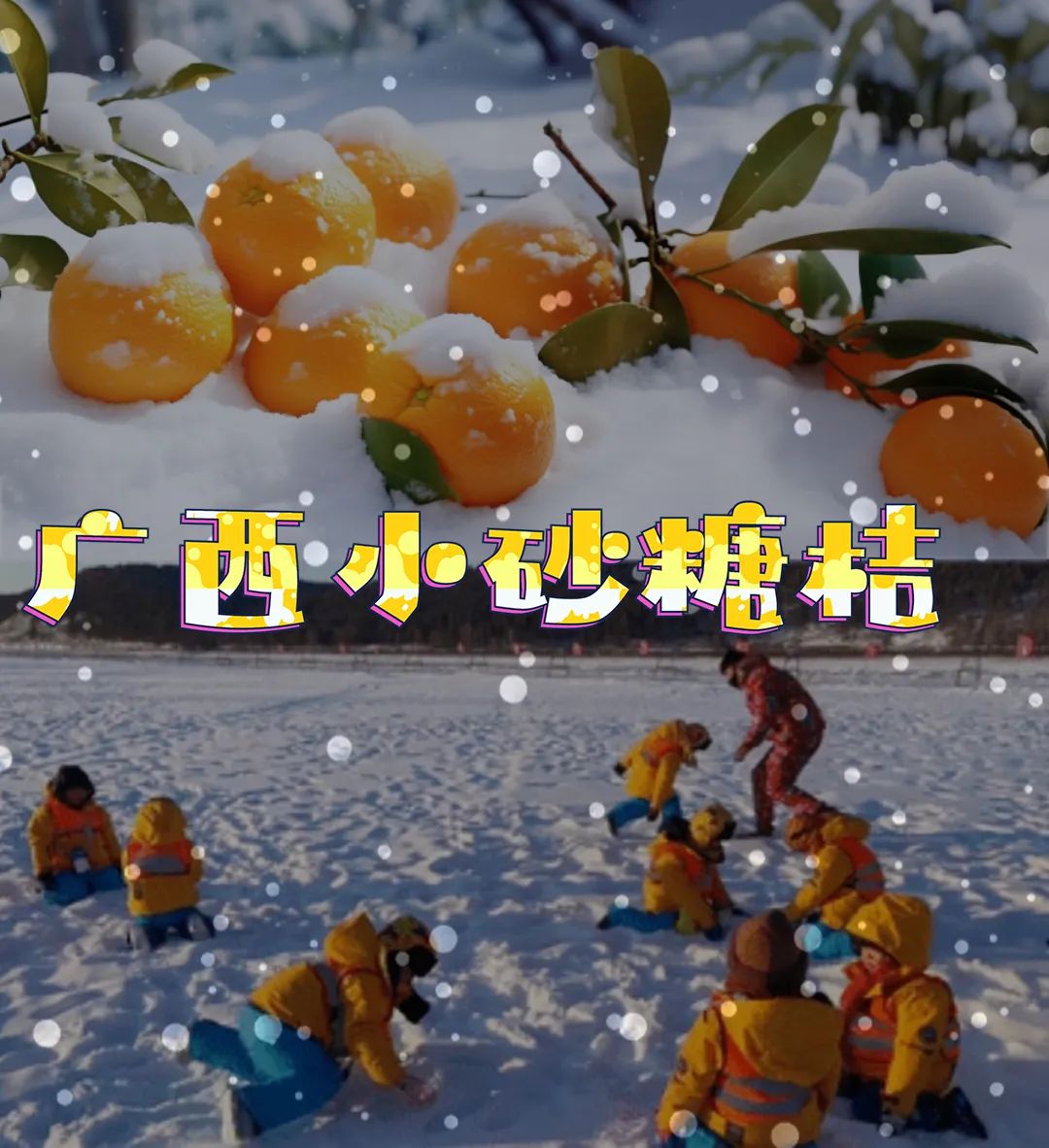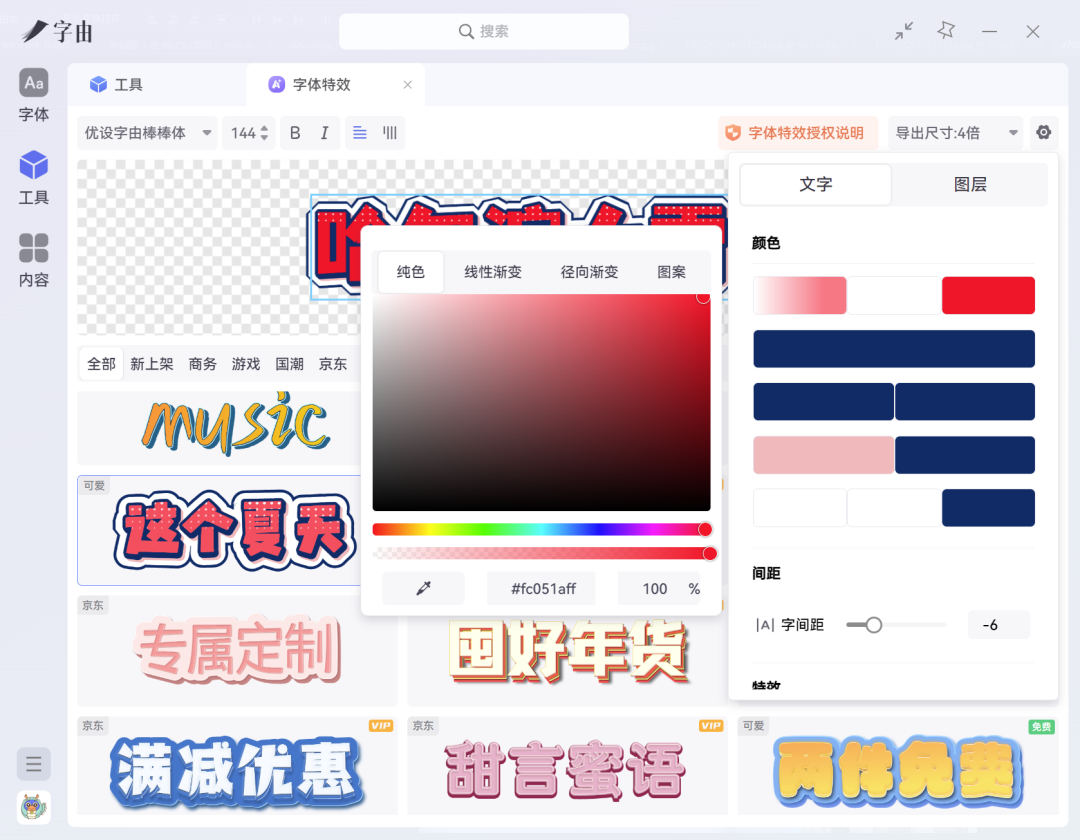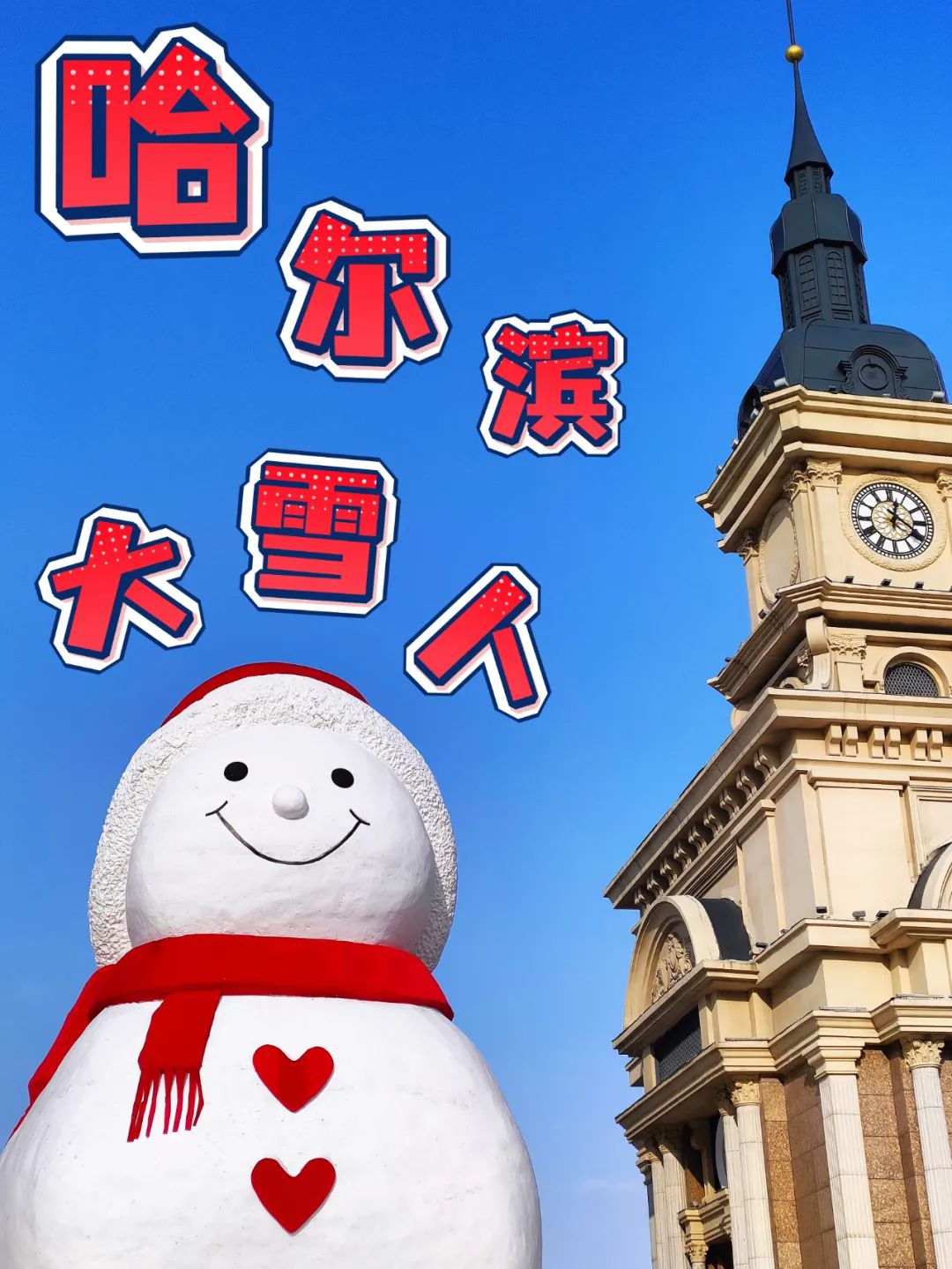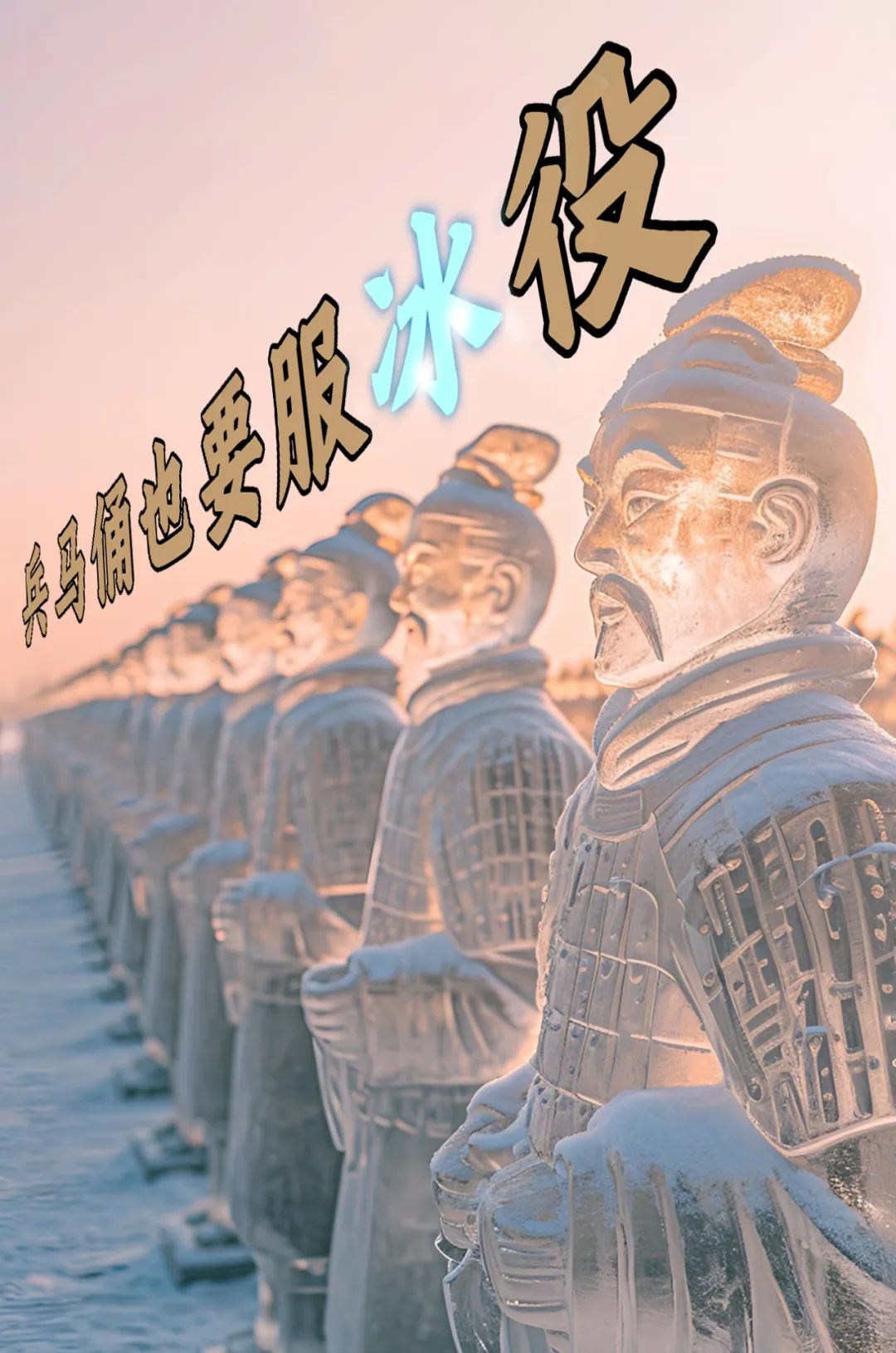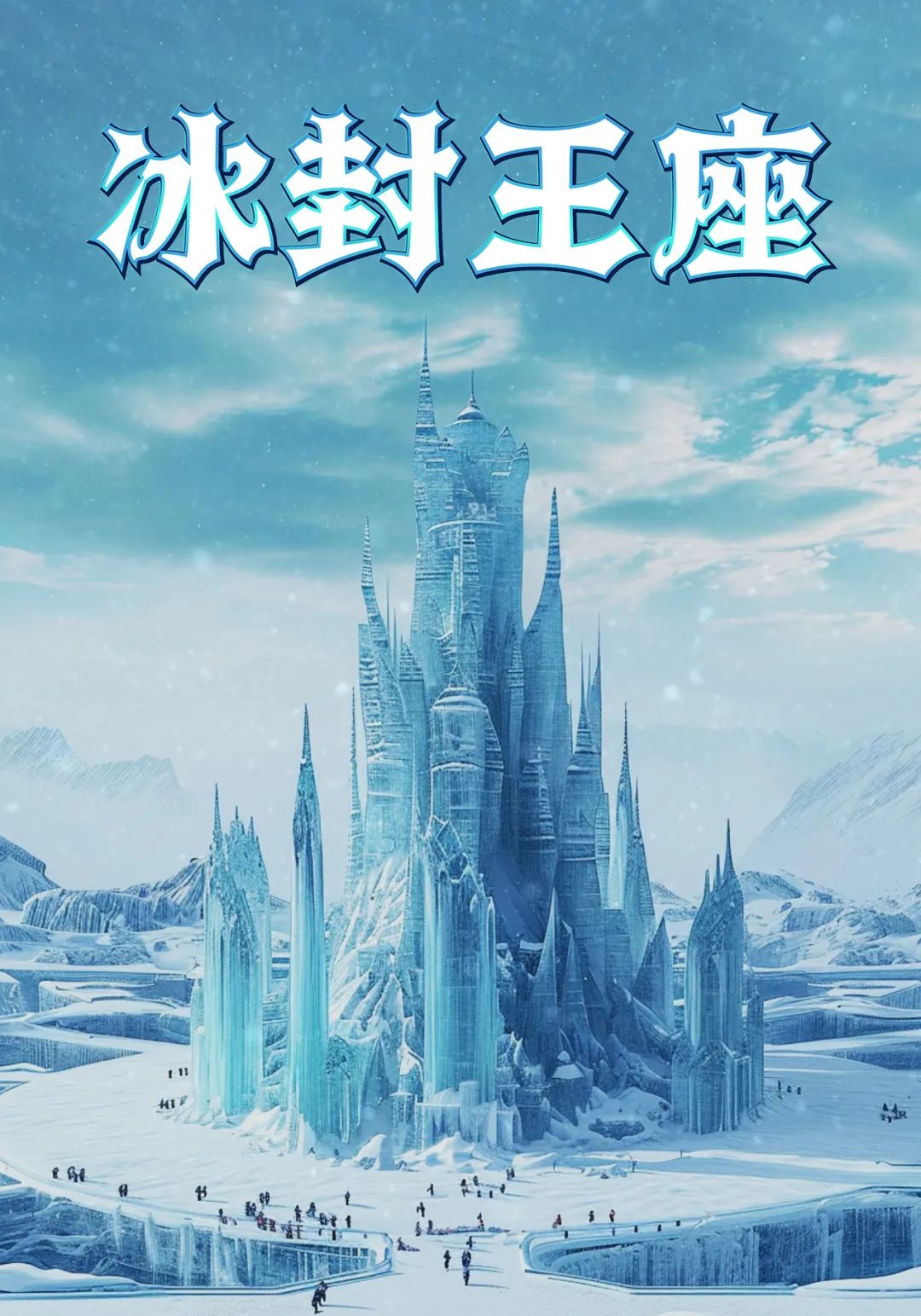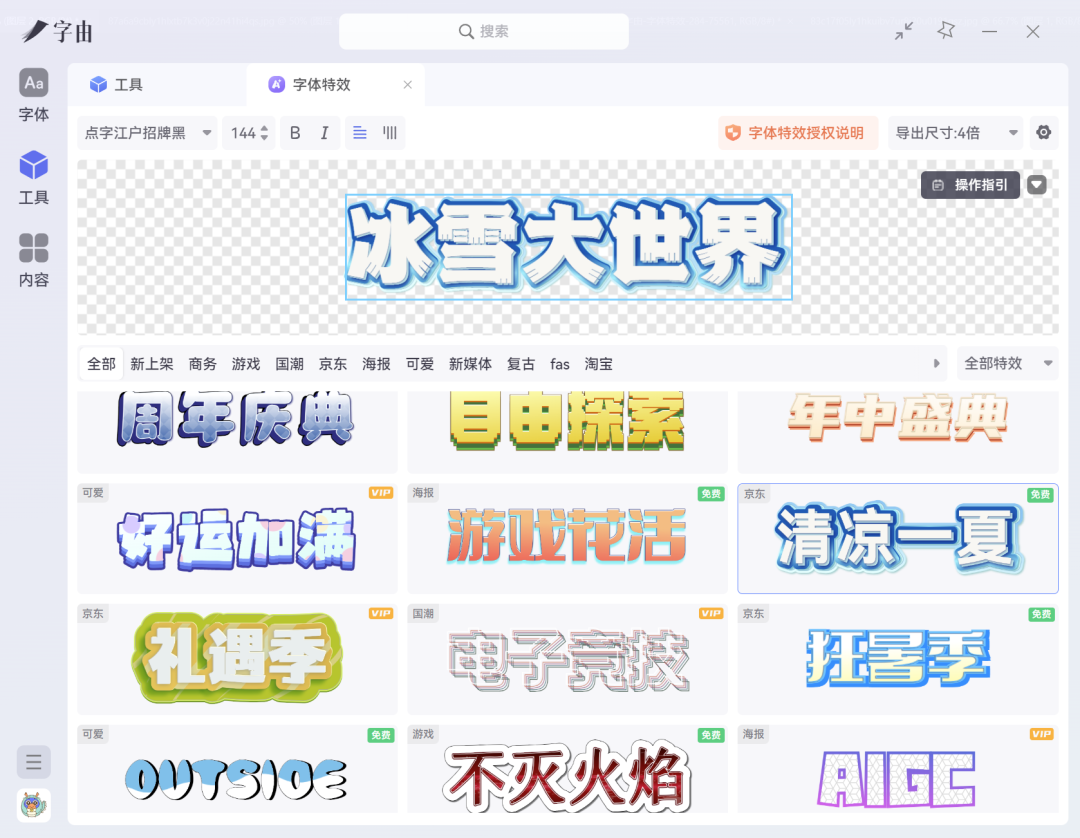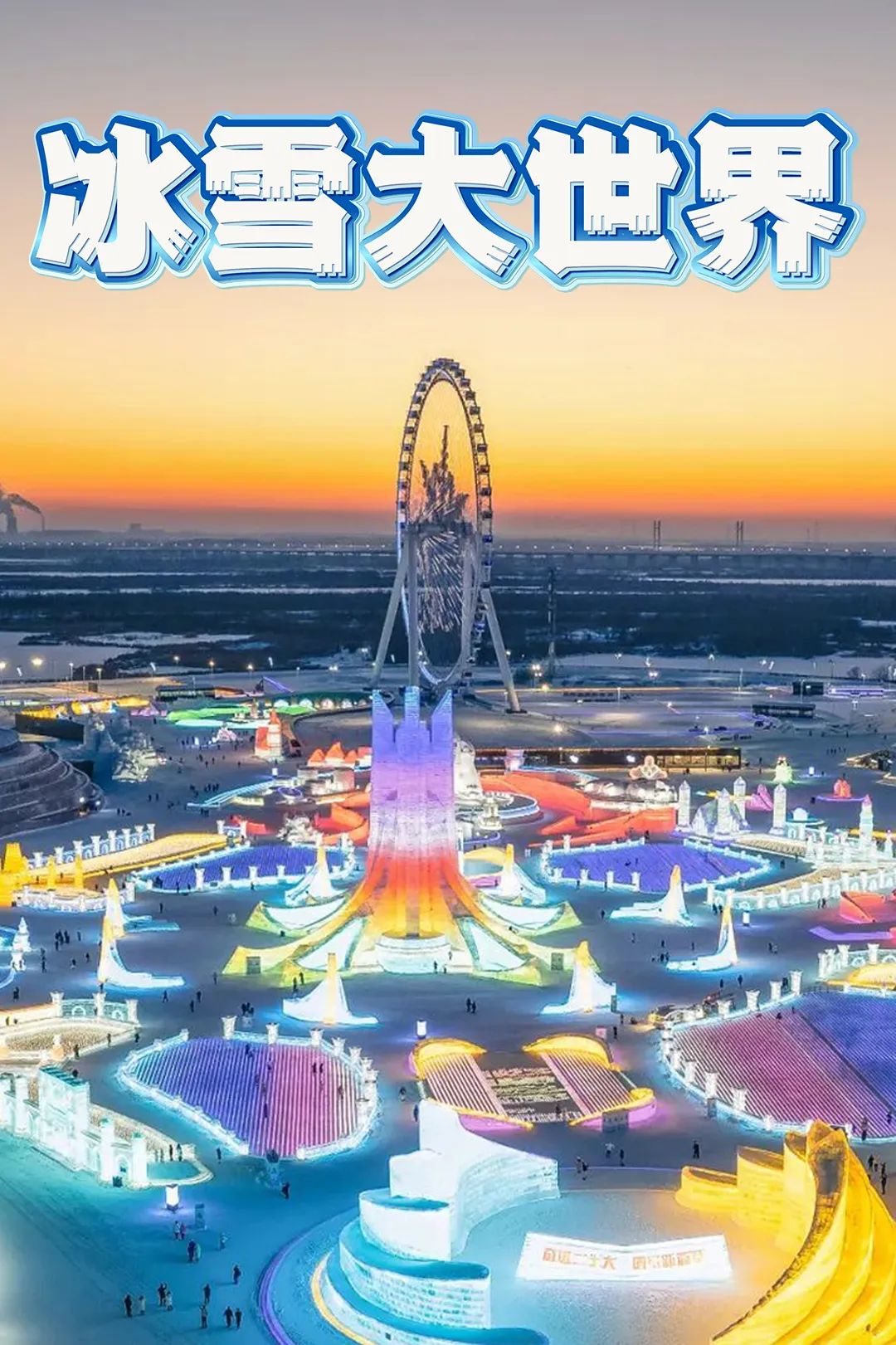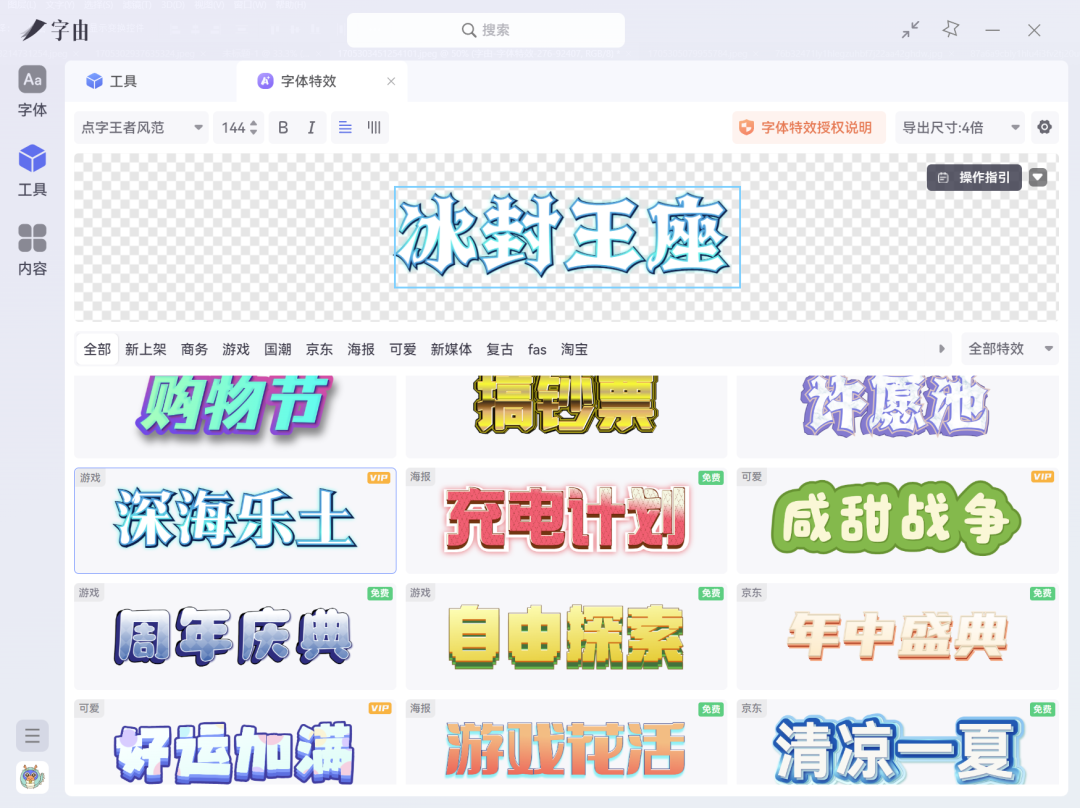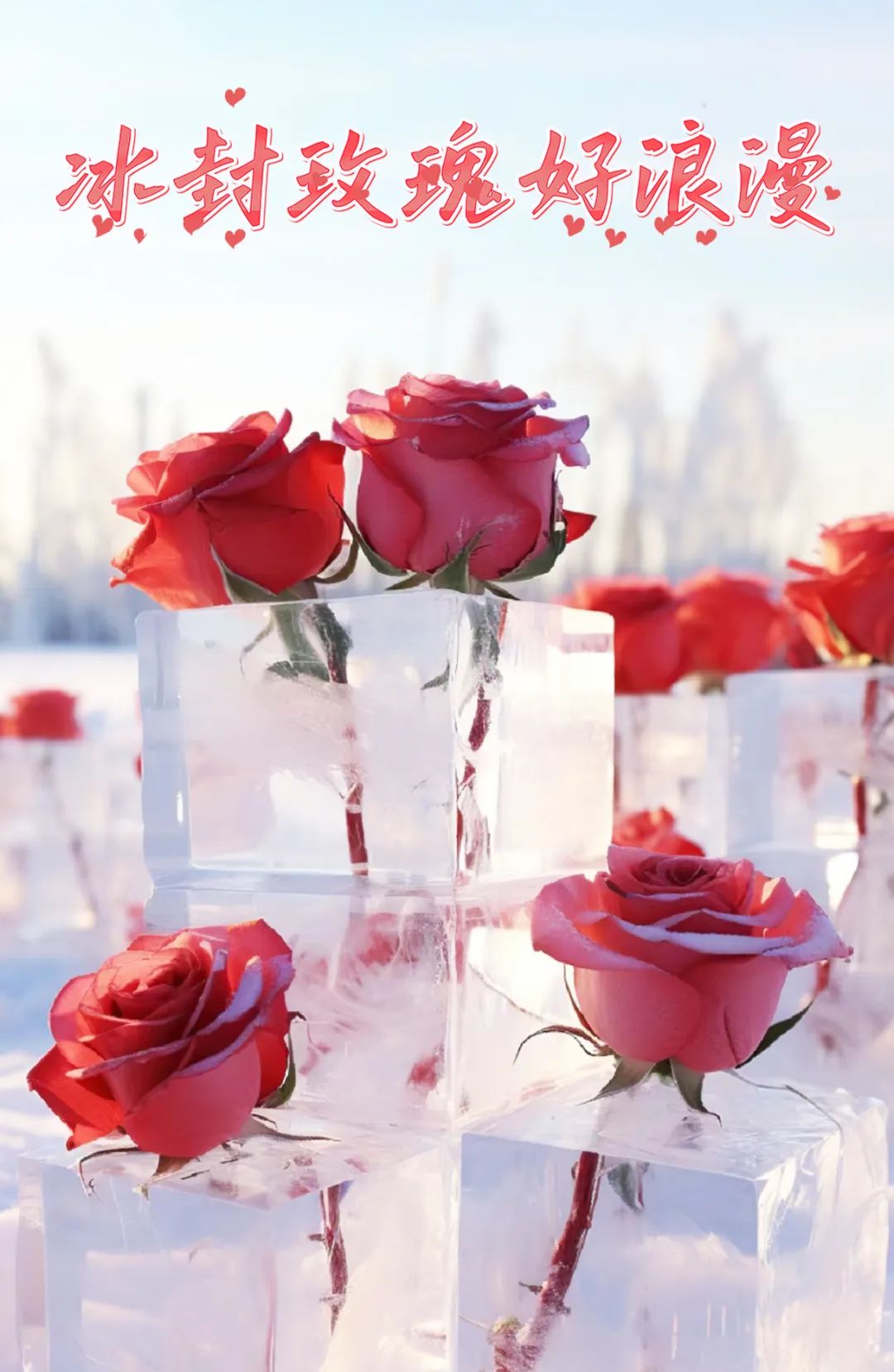
新上架15款字体特效,摸鱼全靠它~
最近哈尔滨太火了,而我只能看着南方小土豆在那边当公主(苦涩)。
没关系,既然没条件,那就创造条件也要上!比如用省事的字体特效,小改一波,望图止渴!
第一个当然是顶流大雪人,用的还是优设字由棒棒体(官方表情包字体),再选一个自带雪花的特效,调整下颜色。
看起来既可爱又适配吧~
尔滨的爆火离不开11个砂糖桔殿下,点字天然呆搭配一个圆点特效,可爱极了。
冰雪大世界向我们证明了,即使是零下二十度,依然可以在这里回归天真。远看有厚度,近看有细节,点字江户招牌黑就是这样,再加一个冷色调的立体特效。
除了玩,冰雕艺术也绝对让你大开眼界,比如“冰”马俑,用两种特效搭配在一起,就可以营造出古今穿梭的感觉,字体选的是点字榜刻体。
就算你不喜欢花,也会被冰封玫瑰狠狠拿捏,那种定格的美,真是太浪漫了,必须配上点字热烈体,再加一点小心心。
虽然冰封王座,看起来有点不真实,但也唯有点字王者风范,能镇得住了,再适配一个有神秘感的游戏特效。
哈尔滨的网红打卡点,怎么少得了圣索菲亚教堂?又好看又好拍的,我选了点字像素之城,来匹配它的繁复。